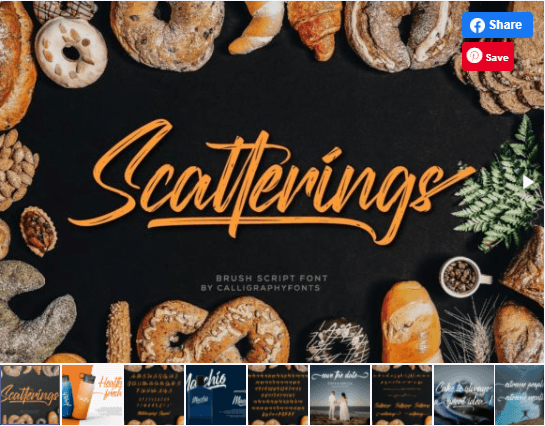
Scatterings Font
Scatterings - красивый и неподвластный времени рукописный шрифт с кисточкой. Это лучший выбор для создания привлекательных логотипов, брендов и цитат. Этот шрифт имеет кодировку PUA, что означает, что вы можете легко получить доступ ко всем глифам и росчеркам!